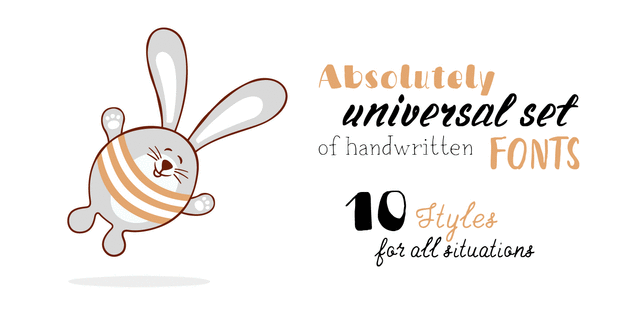
TT Rabbits – сверхэмоциональное рукописное шрифтовое семейство, состоящее из 10 разных шрифтов. Мы объединили эти шрифты по одной общей теме – детство. Используйте эти шрифты для создания любой продукции для детей – детские книжки, приложения для детей, интерьеры детских комнат.
Мы дали каждому кролику уникальное имя. Имена выстроены по буквам латинского алфавита: A — April, B — Bro, C — Chilli, D — Dummy, E — Elf, F — Fatso, G— Goody, H — Hyper, I — Idol, J — Junior. Каждый кролик имеет свой характер, поэтому вы определенно полюбите TT Rabbits. Мы использовали индивидуальный пишущий инструмент для каждого шрифта. Все шрифты изначально создавались на бумаге, а затем оцифрованы.
А какой ваш любимый кролик? Шрифт разработан Иваном Гладких в студии TypeType Fonts в 2016 году.